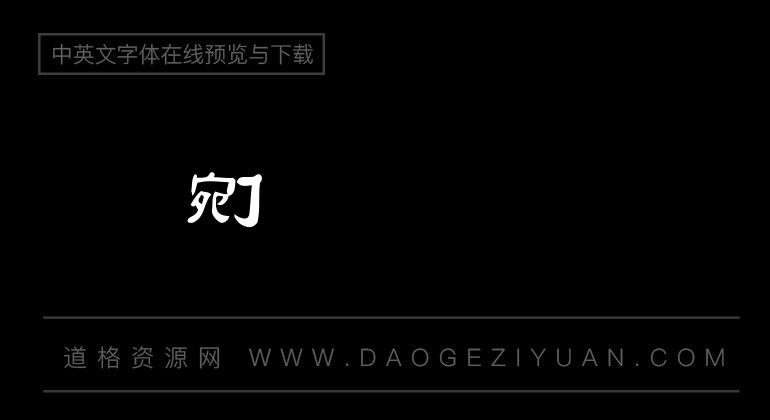
金梅毛隶书
金梅毛隶书是一种中国传统的篆刻字体,它以楷书为基础,受到金文和梅花文影响,融合了其他书体特点,形成了独特的字体风格。金梅毛隶书的特点是字体粗犷,笔画粗细有规律,画面比较有层次感,极具质感。
金梅毛隶书是一款非常不错的手写艺术字体,具有很好的视觉感,适合于文化类的宣传设计、商业类品牌的广告和产品包装设计以及个性化文字排版等较多场景。